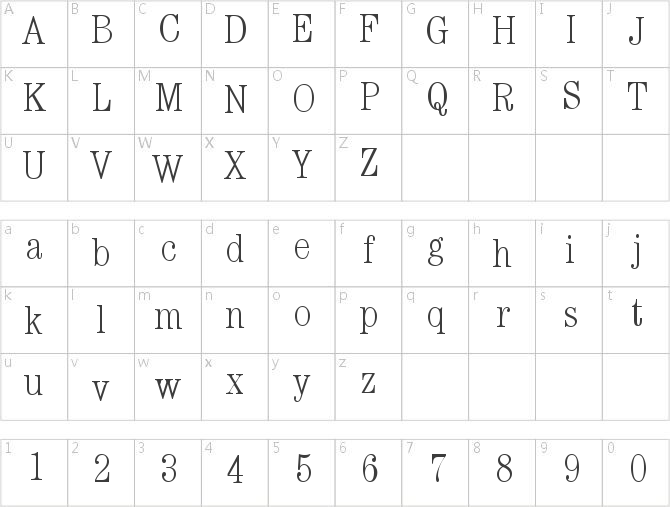
ModernCenturyCondLight
ModernCenturyCondLight介绍
ModernCenturyCondLight字体字库是一款让人赏心悦目、百看不厌的英文字体,适合各类广告和产品包装设计应用,字体大小0.05MB,格式为ttf字体,上传用户是Me / ,yD ,作者/版权方为未知